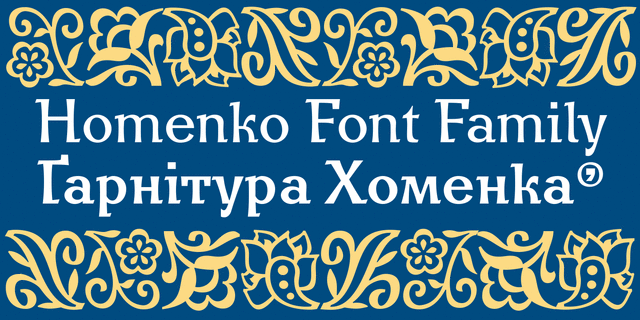
Знаменитая Хоменковская гарнитура, которая еще в советское время продолжала традицию шрифтов с асимметричными засечками (Георгия Нарбута), была завершена известным художником-графиком Василием Хоменко (1912-1984) в 1965 году. Долгое время она оставалась единственной наборной гарнитурой с украинским характером, а также воспроизводилась в декелях для художественно-оформительских работ.
Современная электронная версия была проработана и развита Геннадием Заречнюком. Трансформировавшись в качественную полноценную шрифтовую семью, она отвечает всем требованиям современности.
Шрифт прекрасно подходит для наборных текстов, хорошо читается в мелких кеглях, но, благодаря выразительному характеру, с успехом может быть применен и в акциденции.
Шрифт разработали Геннадий Заречнюк и Виктор Харик по мотивам гарнитуры Василия Хоменко в 2010 году. Затем шрифт переработал и усовершенствовал Константин Головченко в 2020 году.